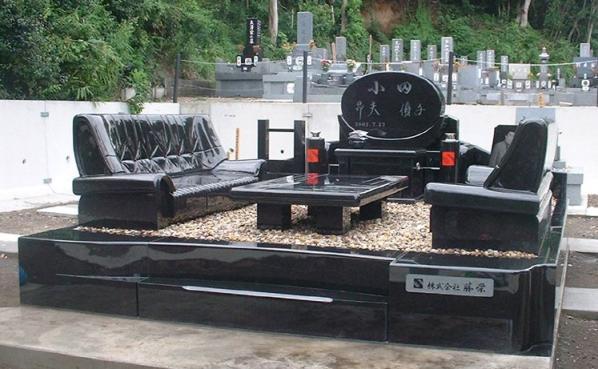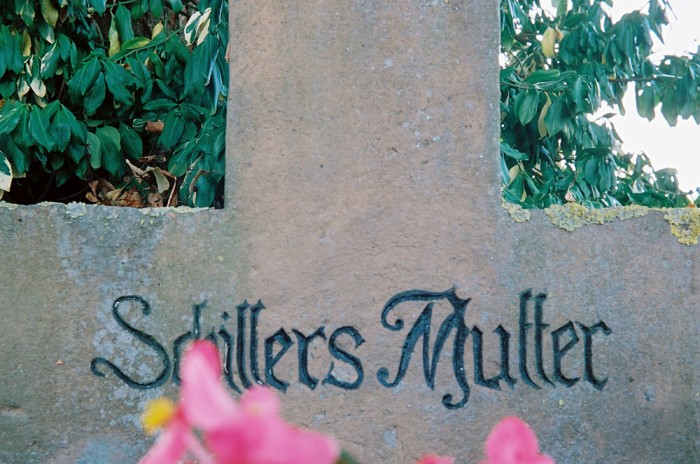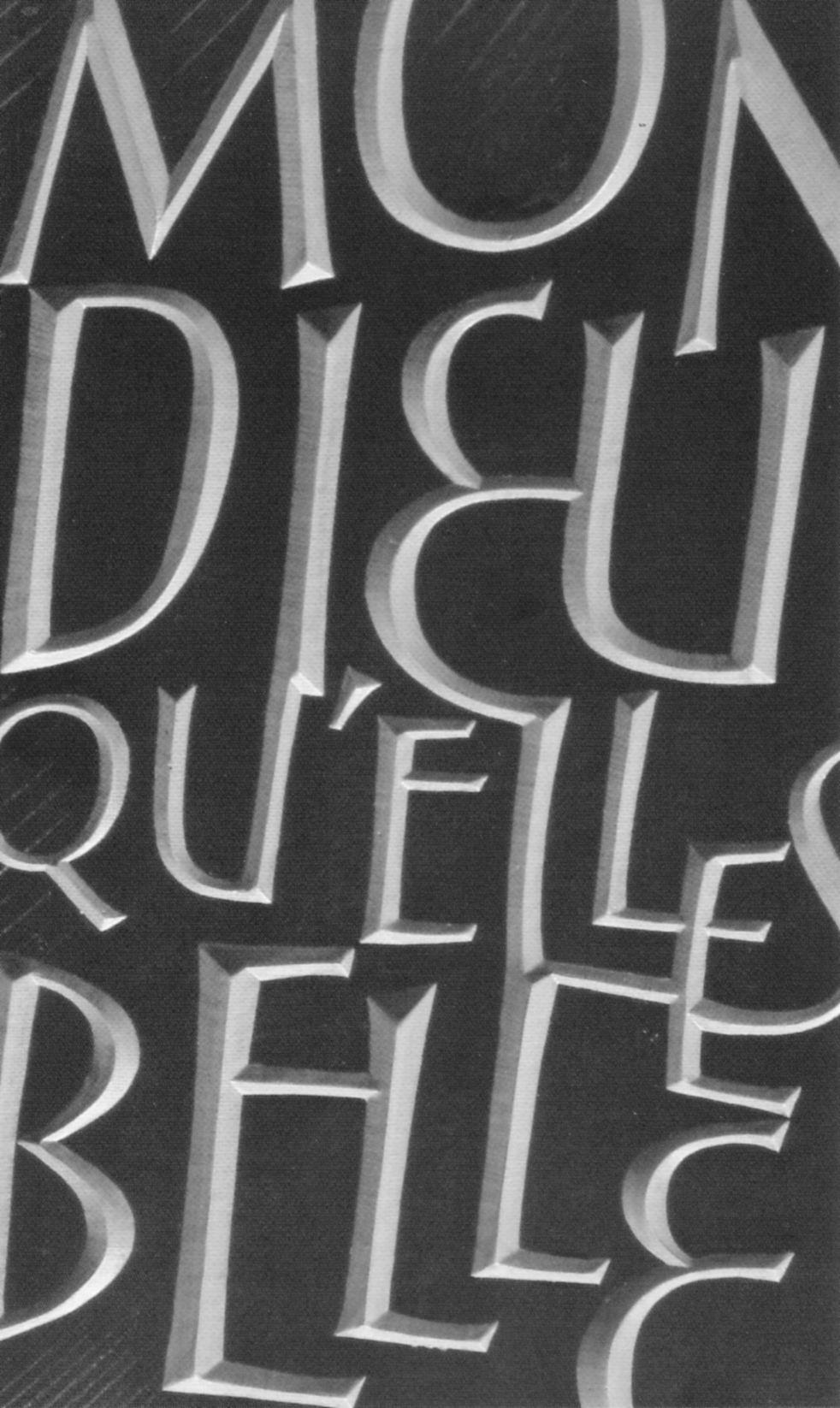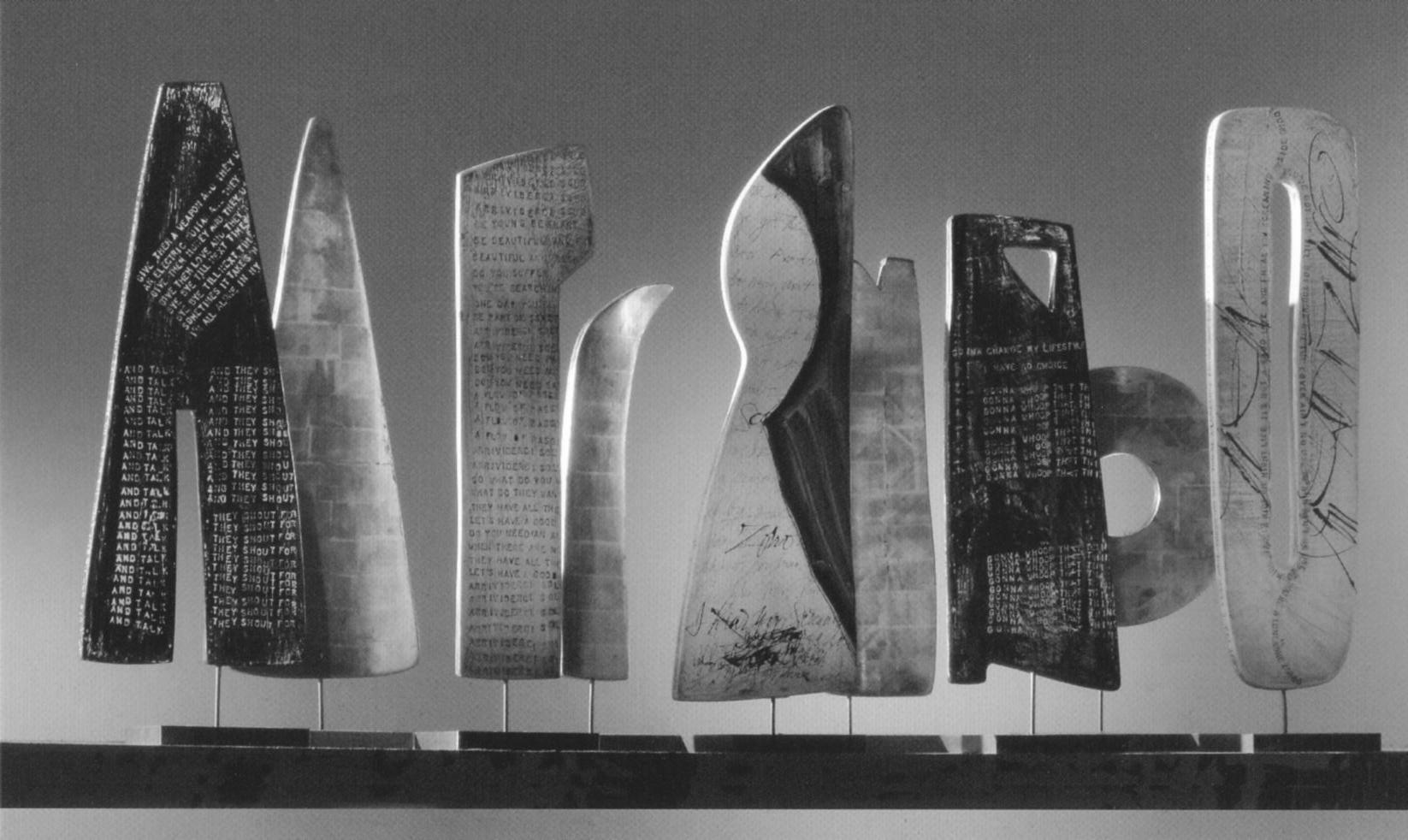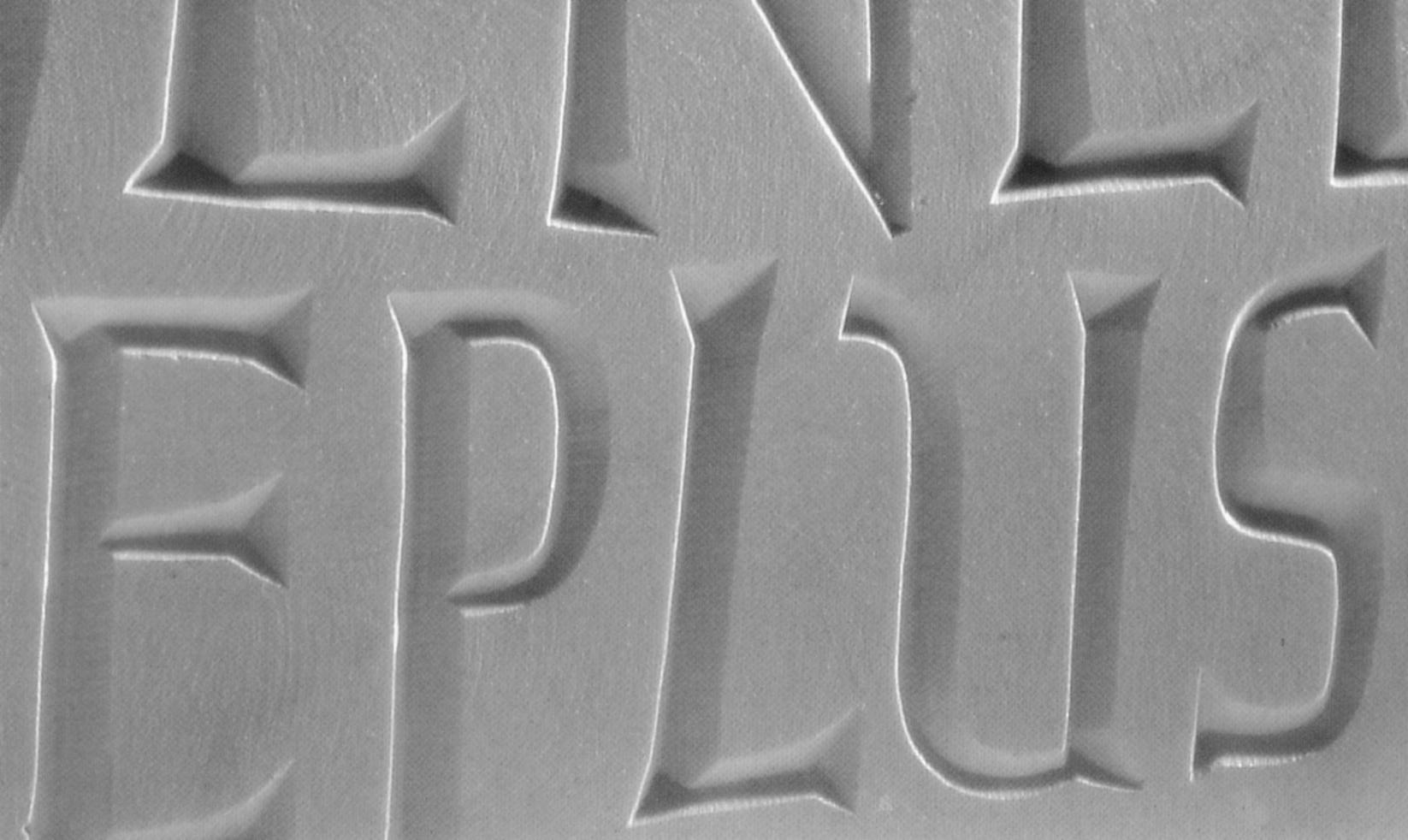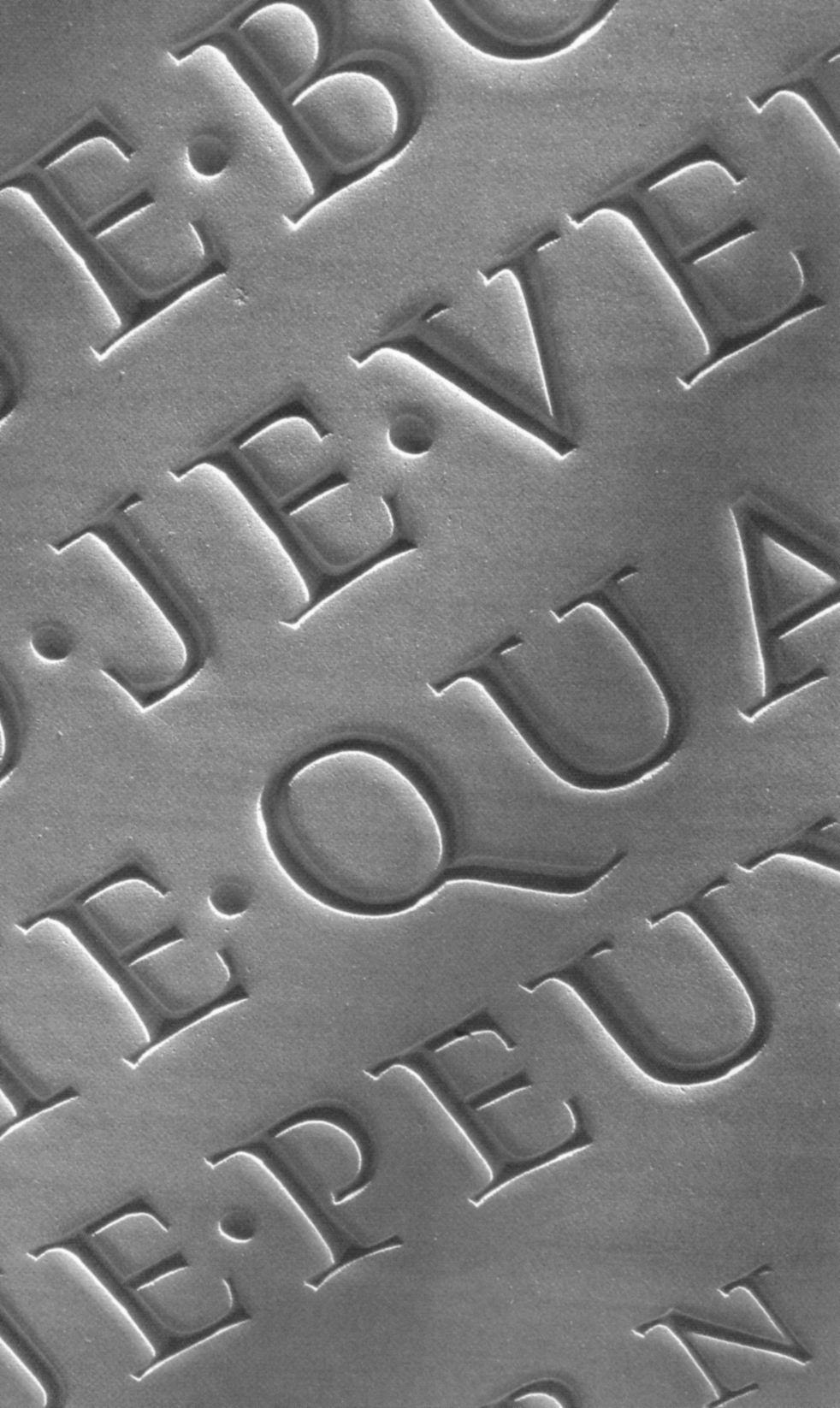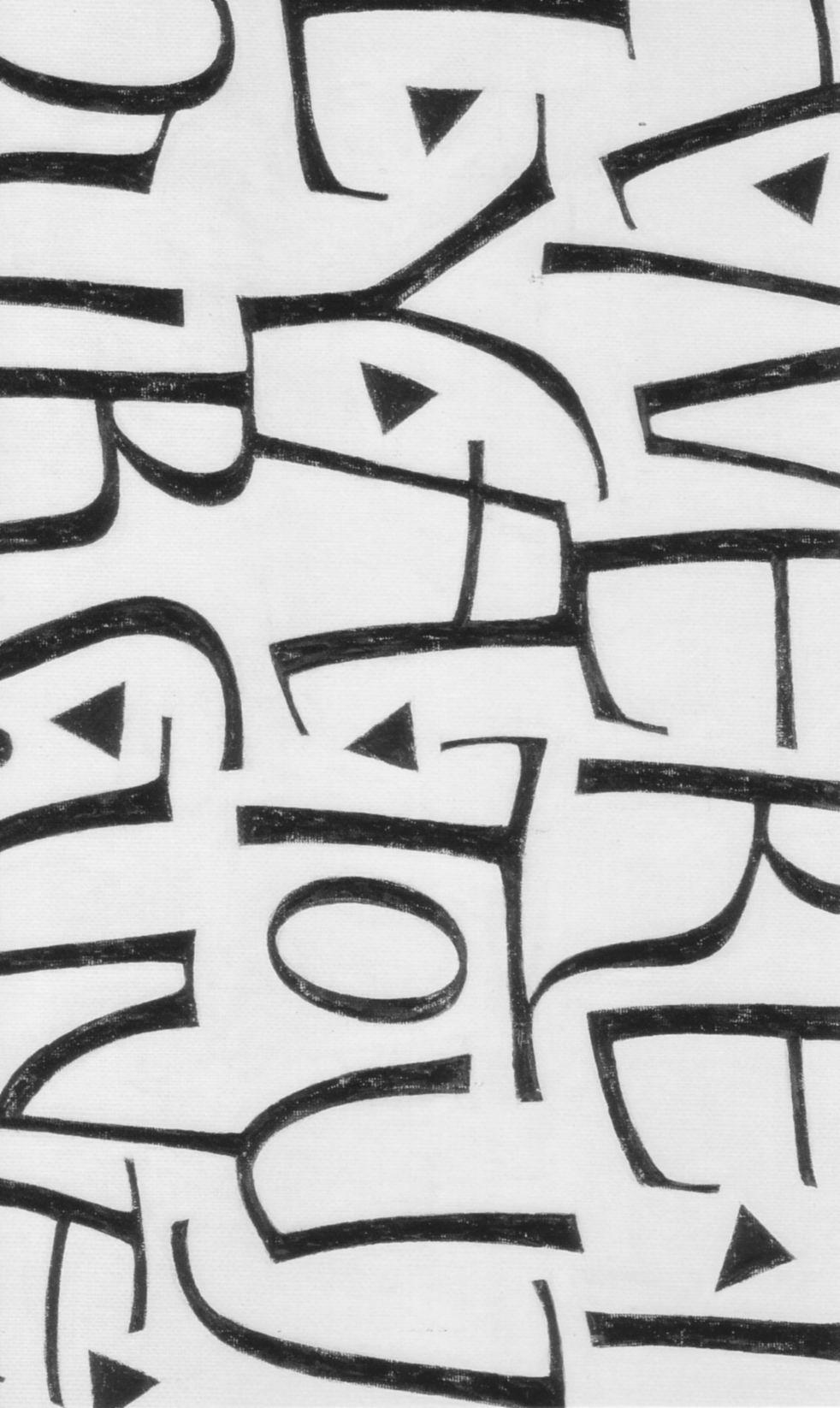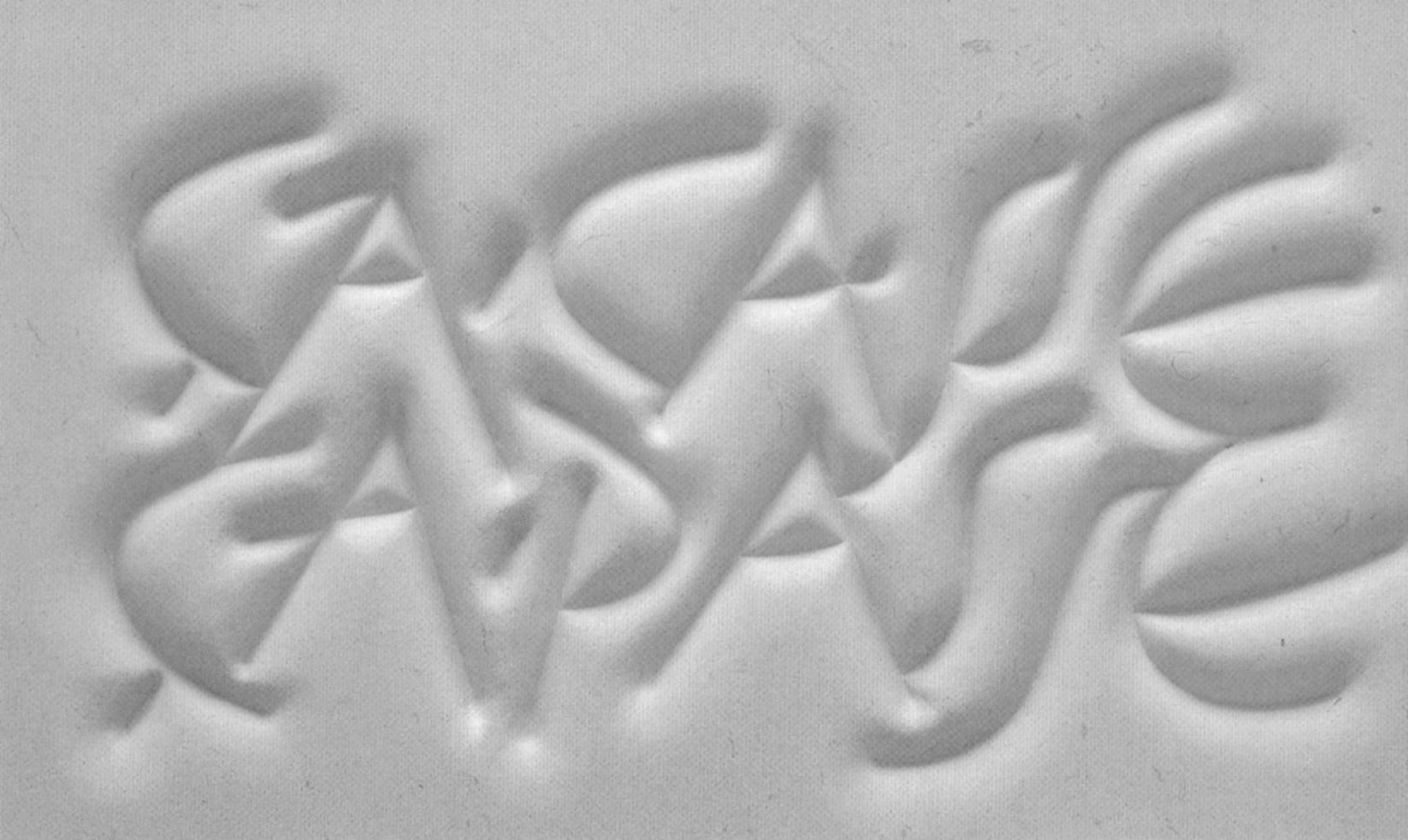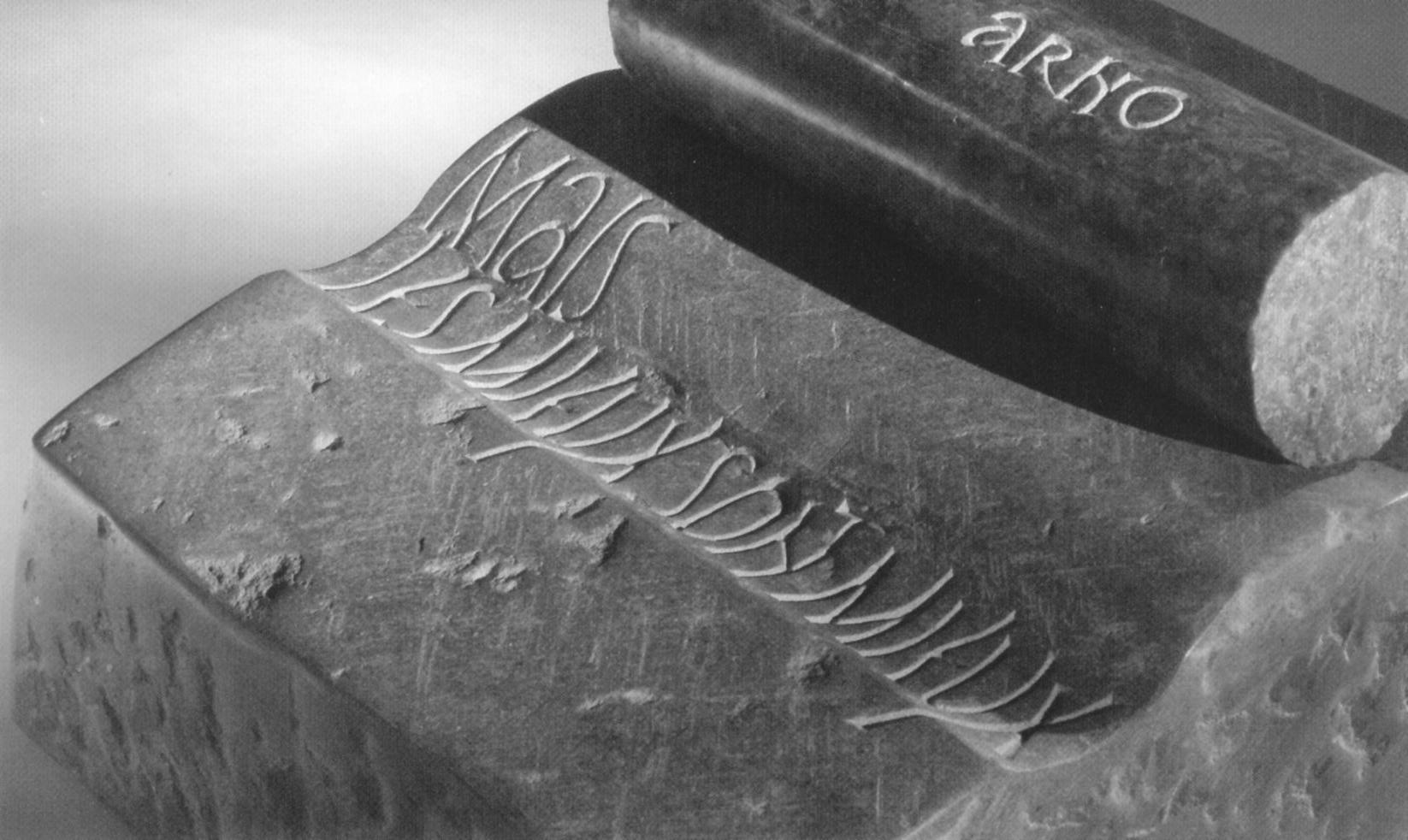
Tombstone-Spotter
Ob das für die Marktforschung interessant ist, daß BMW und Audi weit abgeschlagen hinter Benz liegen? Der hat sogar einen eigenen kleinen Grabstein nur fürs Blechle. Und was es in ikonologischer Hinsicht bedeutet, daß der Wagen in diesem Triptychon den zentralen Platz einnimmt, darüber mögen sich Hagiographen mit Psychologen streiten. Fahrräder sind übrigens ganz selten.
Mörike hat sich übrigens auch mal als Grabstein-Steinmetz versucht. Ich übernehm mal den Beschreibungstext aus meiner flickr-Seite:
Als Mörike Pfarrer in Cleversulzbach war, ließ er die halbvergessene Grabstätte von Schillers Mutter, die 1802 gestorben war, wieder herrichten. Es drängte ihn, auch eine dauerhafte Inschrift anzubringen. Denn wie leicht könnte nach der unglaublichen Gleichgültigkeit, womit man die Sache bisher ignorirte, die Stelle ganz in Vergessenheit kommen! schrieb er 1837 an seinen Freund Hermann Kurz. So restaurierte er ein altes Grabkreuz und ließ dessen alte Inschrift sorgfältig weghauen. Er schlug dann eigenhändig die Worte "Schillers Mutter" ein. Ich habe hierin einige Uebung und sind die Lettern, tief und scharf, Fractur, auch so glücklich gerathen, daß jeder Steinmetz mit Vergnügen sich zu dieser Arbeit bekennen würde, schreibt er dazu.
"tief und scharf, Fractur, auch so glücklich gerathen, daß jeder Steinmetz mit Vergnügen sich zu dieser Arbeit bekennen würde"
Wage ich zu bezweifeln :-)
Wird das M gerade von einem Seepferdchen gefressen? :-?
Vor über 15 Jahren fand irgendwo ein Steinmetz-Symposium unter dem Titel »ARNO« zum Thema Schrift statt. Damals hat bei mir jemand ausgeholfen und mir eine schön gemachte Kassette mit 53 Fototafeln gezeigt. Mir hatte es gefallen und habe diese eingescannt. Vor kurzem habe ich danach recherchiert und auch die recht große Steinmetz-Facebook-Gruppe befragt. Leider ohne Ergebnis. Nehme an, dass es nicht gegen das Interesse der Macher geht. Und diese würden sich ja sicher auch melden. Hier ein paar der Bilder:
Ich erahne schon die nächste Welche-Schrift-ist-das-Frage:
Das muss es doch als Font, am besten als Freefont geben?!